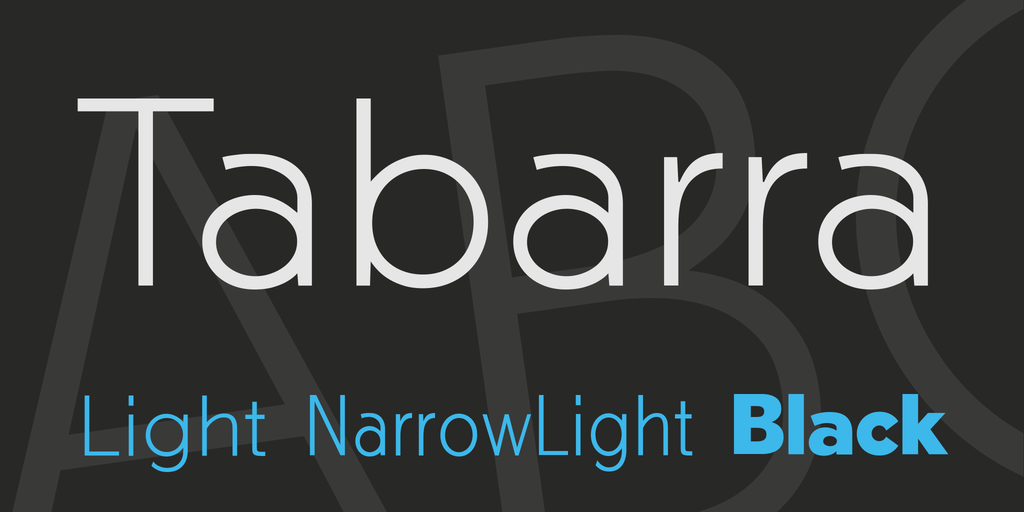
A Tabarra é uma nova adição à família de fóntes sans-serif, criada especialmente para as necessidades do design comercial. Esta versão comercial oferece leitura fácil e clara, com recursos avançados do OpenType que permitem uma composição atraente e sofisticada em textos complexos. A Tabarra não apenas preenche suas demandas de legibilidade, mas também traz um toque de luxo através das decorativas salsichas, que adicionam elegância à sua designação. Para quem busca fontes modernas com uma pitada de sofisticação para textos profissionais ou publicitários, a Tabarra é uma ótima escolha.